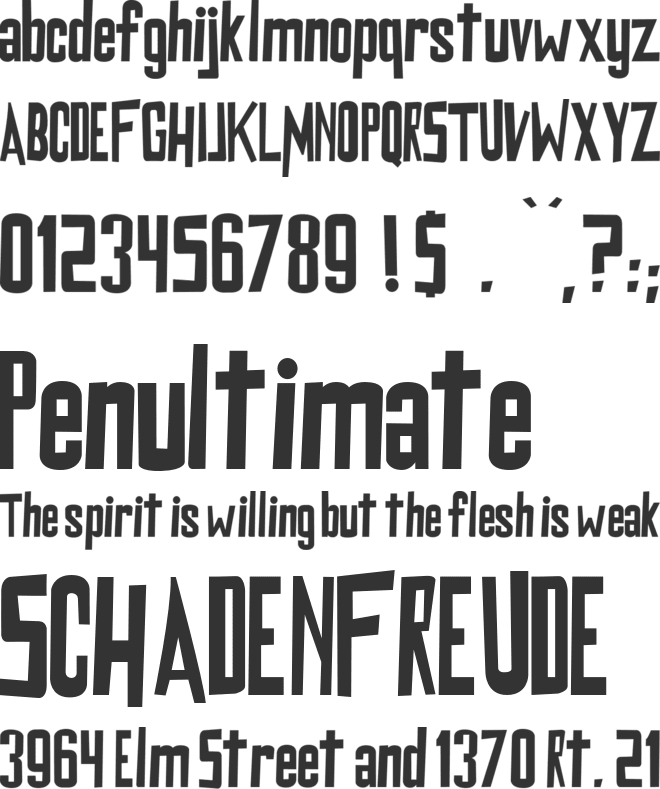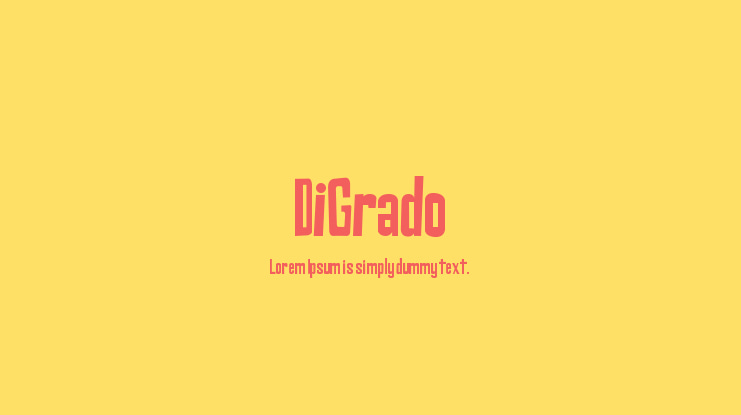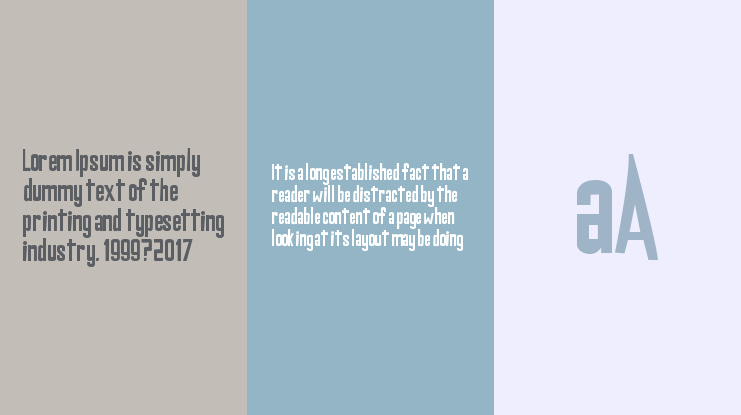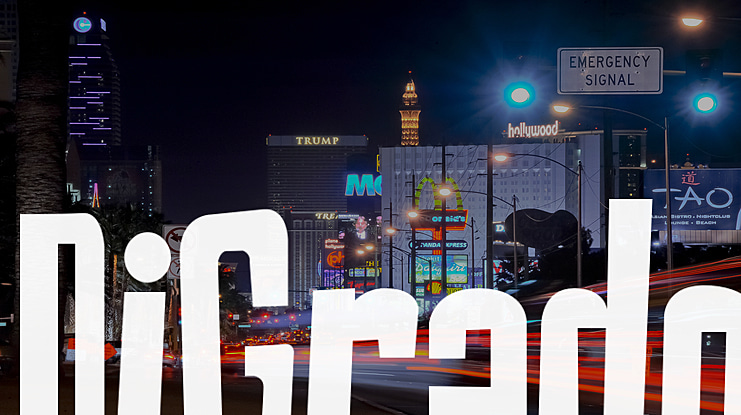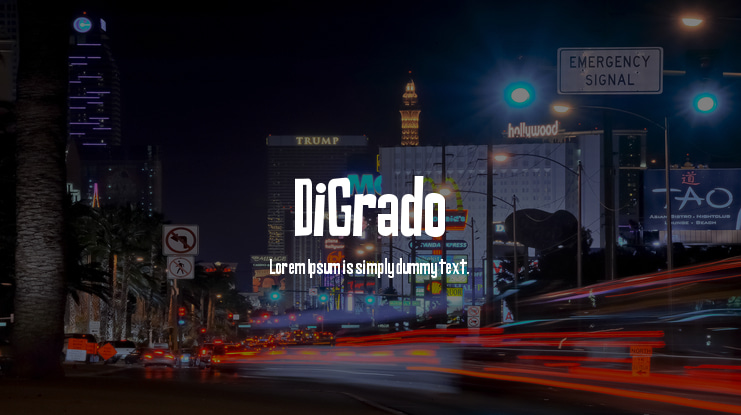
DiGrado Font
Marcio Duarte
Fonte criada a partir da ilustração das letras desenhadas por Vicente Di Grado para as capas dos livros da Editora clube do Livro, durante a década de 1960, no Brasil.